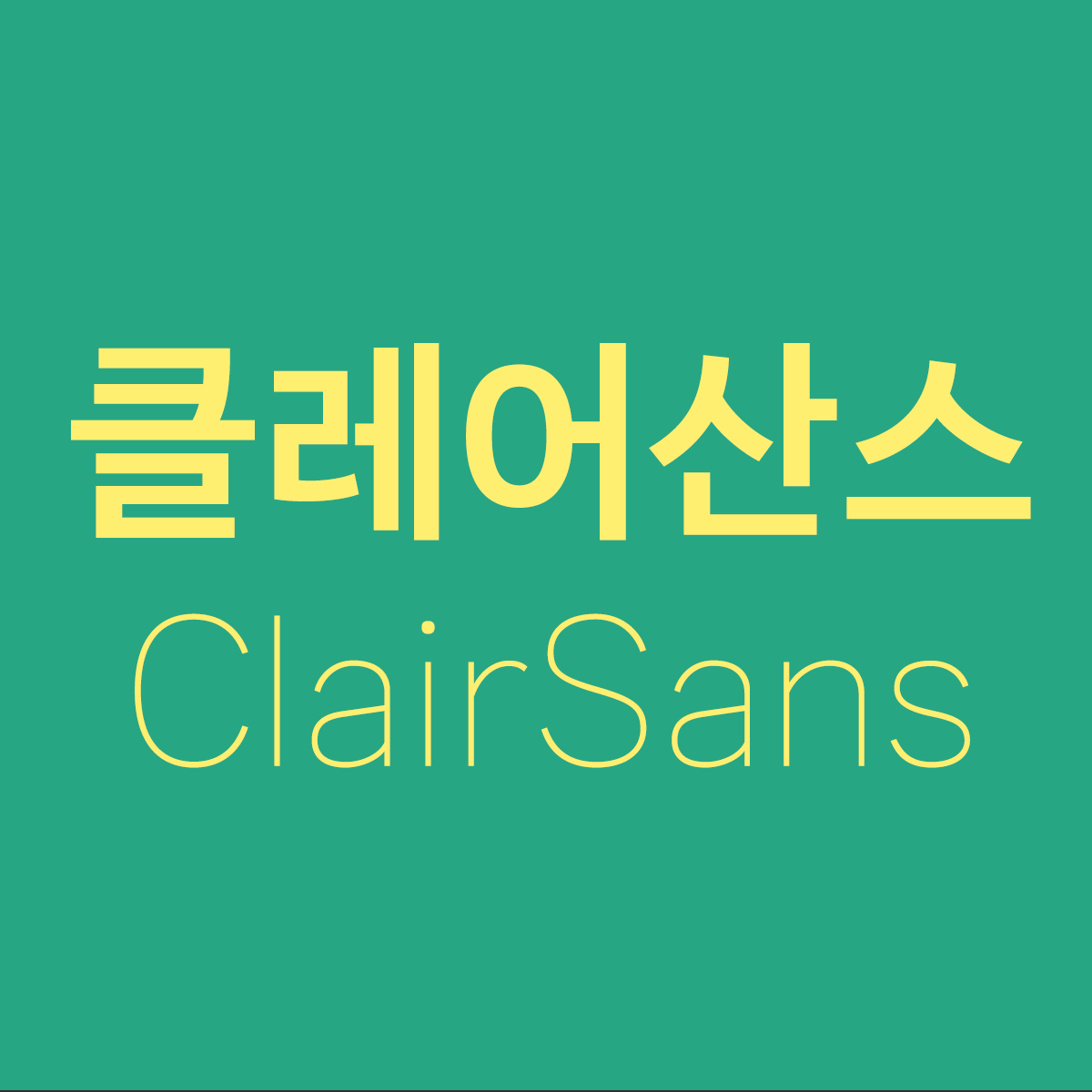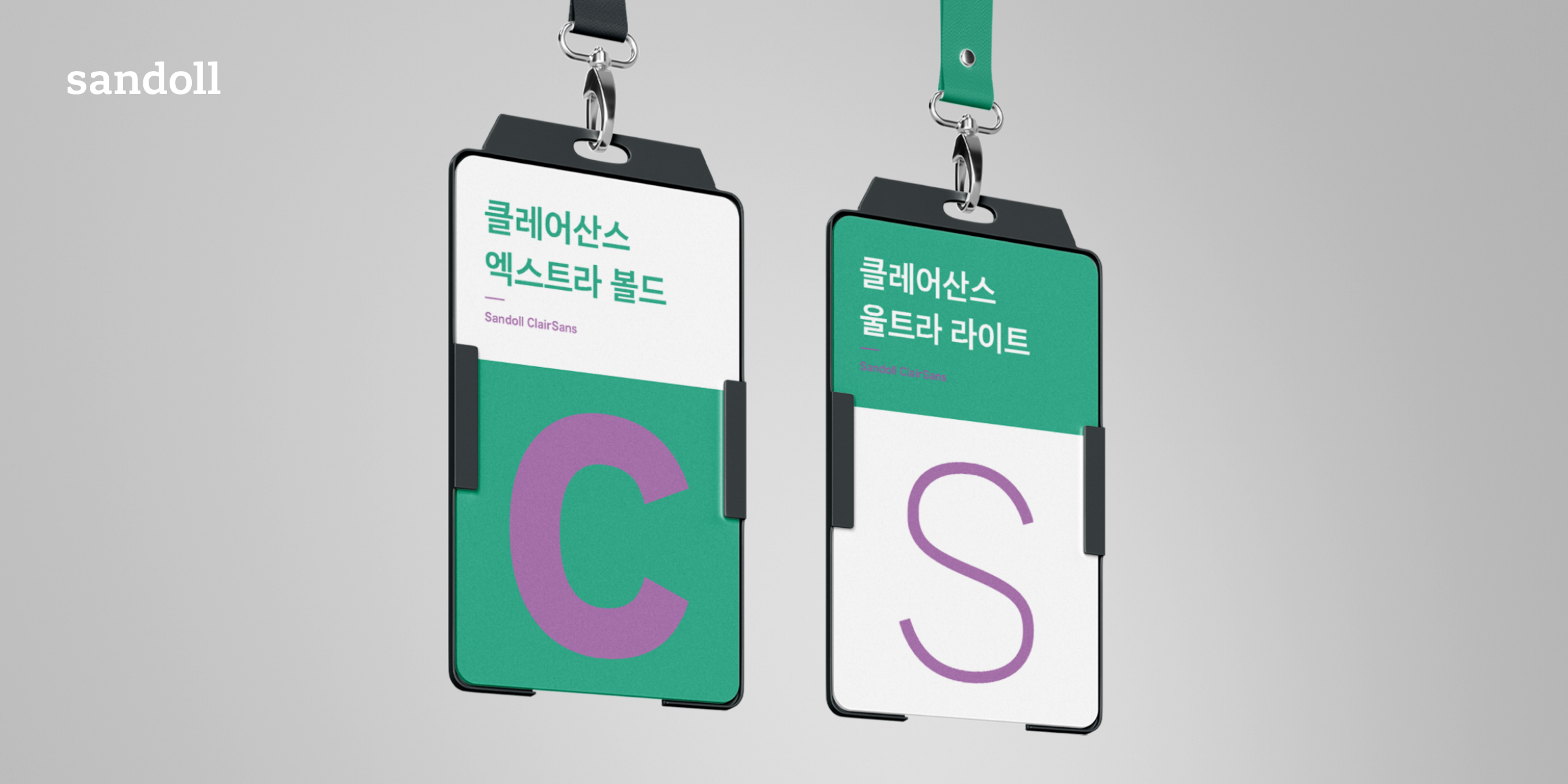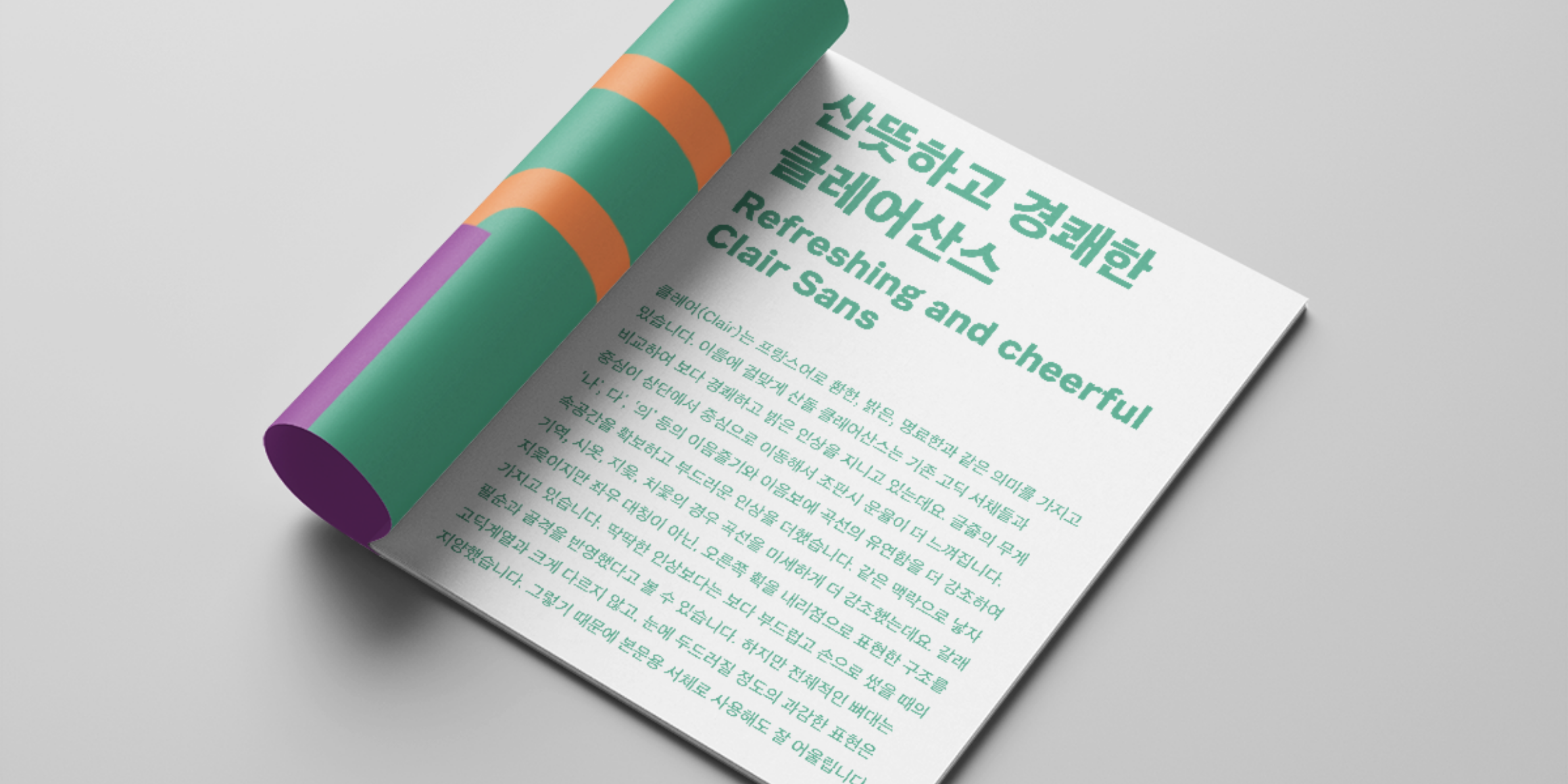
그 이름처럼, 산돌 클레어산스는 기존 고딕 서체들보다 조금 더 경쾌하고 밝은 인상을 지니고 있습니다.
밝고 산뜻한 인상을 주기 위해 ‘나’, 다’, ‘의’ 등의 이음줄기와 이음보 곡선을 둥글게 표현했습니다. 같은 맥락으로 낱자 기역, 시옷, 지읒, 치읓의 경우 곡선을 미세하게 더 강조되었습니다. ㅅ,ㅈ,ㅊ의 경우 다소 딱딱한 인상을 피하기 위해 비대칭인 구조를 택했고, 이응은 타원형의 네 귀퉁이의 속공간을 좀 더 바깥으로 밀어내어 속공간을 조금 더 넓혔습니다. 획이 많고 복잡한 ㅃ, ㅆ등의 쌍닿자들은 단순화 시켜 깨끗한 인상을 더했습니다. 전체적인 뼈대는 고딕계열과 크게 다르지 않고, 눈에 거슬릴 정도의 표현은 지양했습니다. 라틴과 숫자 및 부호류는 산돌 CompSans를 기반으로 클레어산스 한글에 어울리게 미세하게 수정되었습니다.